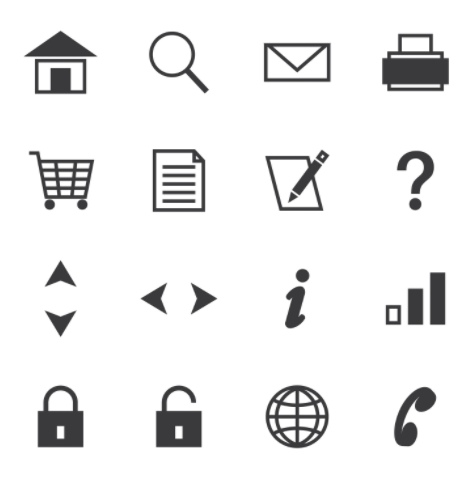
Font Awesome è una libreria CSS che ci permette di proiettare caratteri e i simboli sui siti web. In altre parole, se vuoi aggiungere icone ai tuoi menu, titoli, ecc. sul tuo sito web, non devi cercare costantemente immagini con estensione .png. Ti sarà sufficiente utilizzare Font Awesome.
FontAwesome è un framework di font che semplifica l'aggiunta di simboli. Questi sono i tuoi menu, intestazioni, ecc. sul tuo sito web. Se vuoi aggiungere un'icona, non devi continuare a cercare immagini con estensione ”.png”.
Prima del rilascio di FontAwesome e delle sue alternative, dovevamo progettare i simboli che avremmo utilizzato per le nostre applicazioni in qualsiasi editor visivo e utilizzarli con output in formato PNG o SVG. Quindi ci è voluto del tempo per creare le icone. Di conseguenza, le icone che abbiamo creato hanno causato problemi come il caricamento lento del sito Web. Font Awesome ci offre una soluzione efficacie e ci velocizza sia il lavoro che il sito web.
Oltre al supporto CSS, ora c'è il supporto SVG, come puoi vedere, ci sono Font Awesome Icon Pack che puoi utilizzare su siti Web e applicazioni sviluppate. FontAwesome è un font simbolico. Ha più di 4500 icone nella versione pro e più di 1400 icone gratuite. Quando colleghi il tuo sito a FontAwesome, puoi accedere a qualsiasi icona con un semplice tag HTML.
I vantaggi di Font Awesome
- Una libreria ben oltre di 5900 icone gratuite di quali alcune in versione premium.
- Ogni icona è facile da includere al tuo sito web.
- Possibilità di ridimensionare le icone come preferisci.
- È facile aggiungere icone ovunque.
- Non esiste un apprendimento molto gratificante.
- Il design è coerente, quindi tutto adattabile.
- Il design è molto minimale, quindi le icone possono essere utilizzate per vari scopi.
- Non importa quanti simboli hai bisogno, FontAwesome può fornirli gratuitamente.